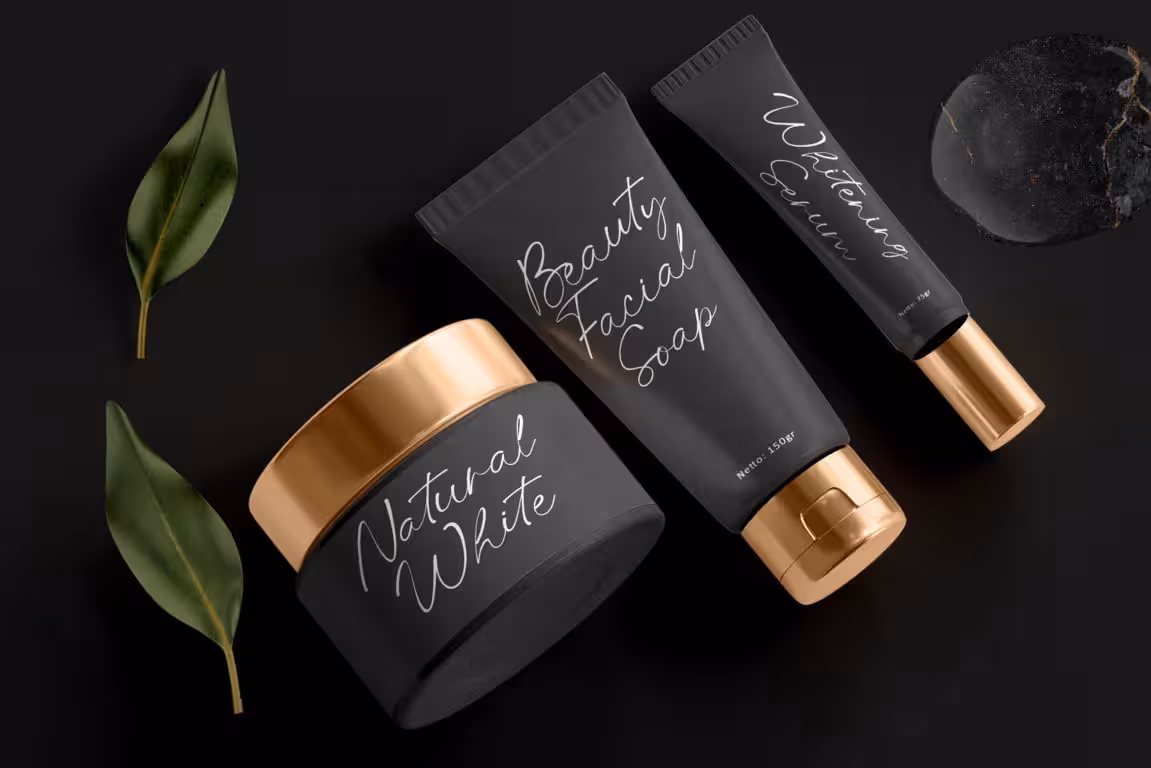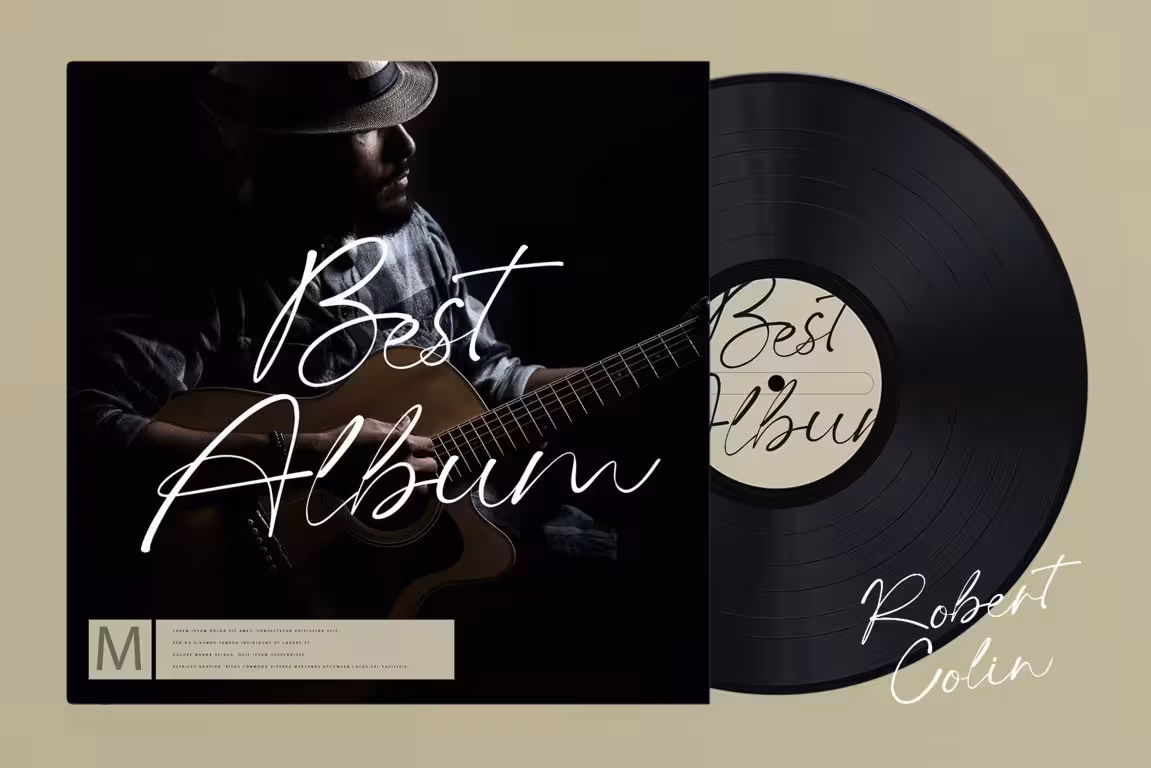
Giới thiệu về Font TF Arveton Việt hóa
TF Arveton Việt hóa là một font chữ ký (signature font) nổi bật với thiết kế thanh mảnh, uyển chuyển và đầy tinh tế. Font này mang đến vẻ ngoài mềm mại, sang trọng và rất riêng, gợi cảm giác như một chữ ký được viết tay một cách tự nhiên và đầy cảm xúc. Đặc biệt, bộ font còn sở hữu một loạt glyphs (ký tự đặc biệt) đẹp mắt, giúp tăng tính sáng tạo và độc đáo cho các thiết kế.
Với đặc điểm là nét viết tay mềm mại, phong cách tự nhiên và tính thẩm mỹ cao, Arveton là lựa chọn hoàn hảo cho các ấn phẩm muốn truyền tải sự nhẹ nhàng và phong cách, đặc biệt là trong các lĩnh vực:
• Thiết kế mỹ phẩm: Hoàn hảo cho bao bì, nhãn mác, hoặc các ấn phẩm quảng cáo của các sản phẩm làm đẹp, mỹ phẩm cao cấp. Font này giúp truyền tải vẻ đẹp tinh tế, sang trọng và độc quyền của sản phẩm, nâng tầm giá trị thương hiệu.
• Thiết kế album ca nhạc: Lý tưởng để sử dụng cho tên album, tên bài hát, hoặc chữ ký của nghệ sĩ trên bìa album hoặc các ấn phẩm truyền thông. Nét chữ uyển chuyển của font sẽ làm tăng tính nghệ thuật và cảm xúc cho sản phẩm âm nhạc, tạo dấu ấn cá nhân đậm nét.
• Thiết kế logo và nhận diện thương hiệu: Phù hợp để tạo logo, tagline hoặc bộ nhận diện thương hiệu của các công ty, doanh nghiệp muốn truyền tải sự tinh tế, độc đáo và một chút hoài cổ, đặc biệt là các thương hiệu liên quan đến thời trang, đồ handmade, hoặc các sản phẩm mang tính di sản.
• Thiết kế thiệp và nội dung: Tuyệt vời để viết lời mời, lời chúc, hoặc các câu trích dẫn đầy cảm hứng, slogan hoặc các dòng chữ cần sự nổi bật và mang tính biểu cảm trên mạng xã hội hoặc các ấn phẩm khác, đặc biệt khi kết hợp với hình ảnh mang hơi hướng cổ điển hoặc nghệ thuật.
Với TF Arveton Việt hóa, bạn có thể dễ dàng thổi hồn tinh tế, nhẹ nhàng và vẻ đẹp hoàn hảo vào các thiết kế, tạo ra những sản phẩm không chỉ đẹp mắt mà còn đầy cảm xúc và sức hút đặc biệt.